- 字由:客户端内将字体清晰划分为“免费商用”“商业授权”“个人非商业授权”“未授权”四大类别。绿色标签的字体可放心用于商业项目。同时收录了思源黑体、阿里巴巴普惠体等3000+款免费商用字体,一键激活即可在PS、AI等软件中使用,无需手动下载安装。用字由选字,相当于给每一款字体都配了一张“身份证”。
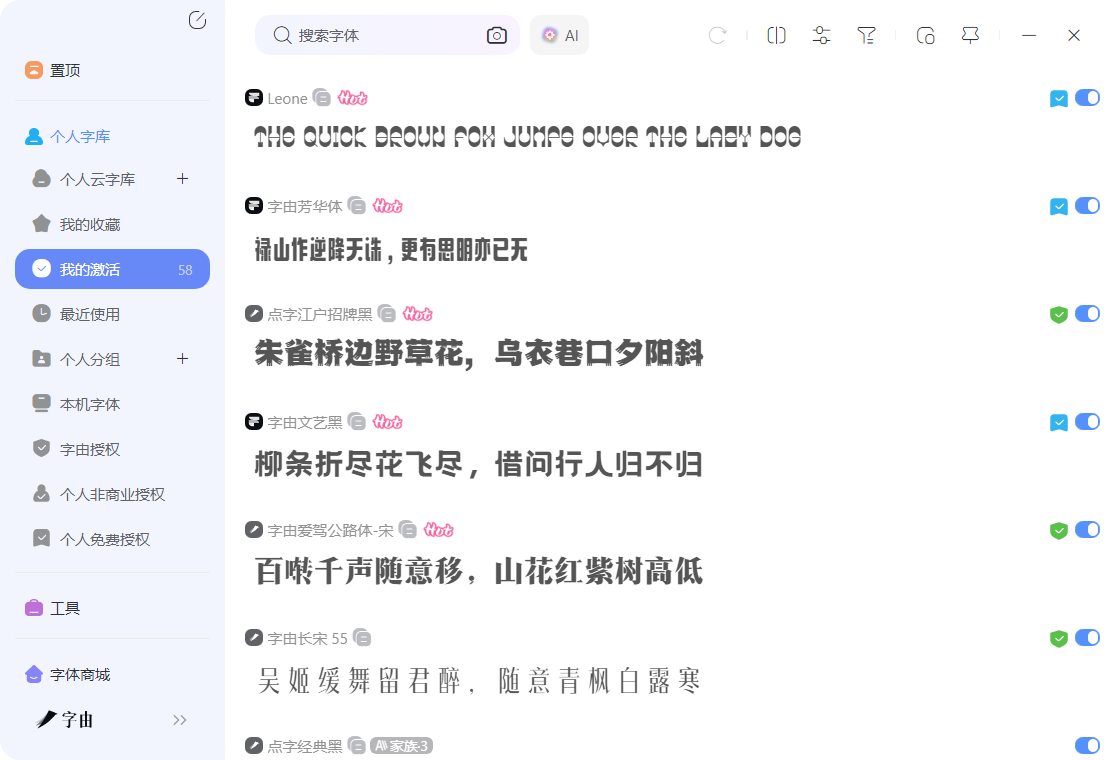
把“安全字体清单”作为第一道防线,让授权状态清晰可见;用字由这类工具作为第二道防线,让每一款字体的“身份”透明化;用规范的外包管理作为第三道防线,让合作方也承担起应有的责任。
字体虽小,版权事大。从今天开始,把“先查权、后使用”写进你的设计工作流。这不仅是保护自己,更是对每一位字体设计师劳动成果的尊重。